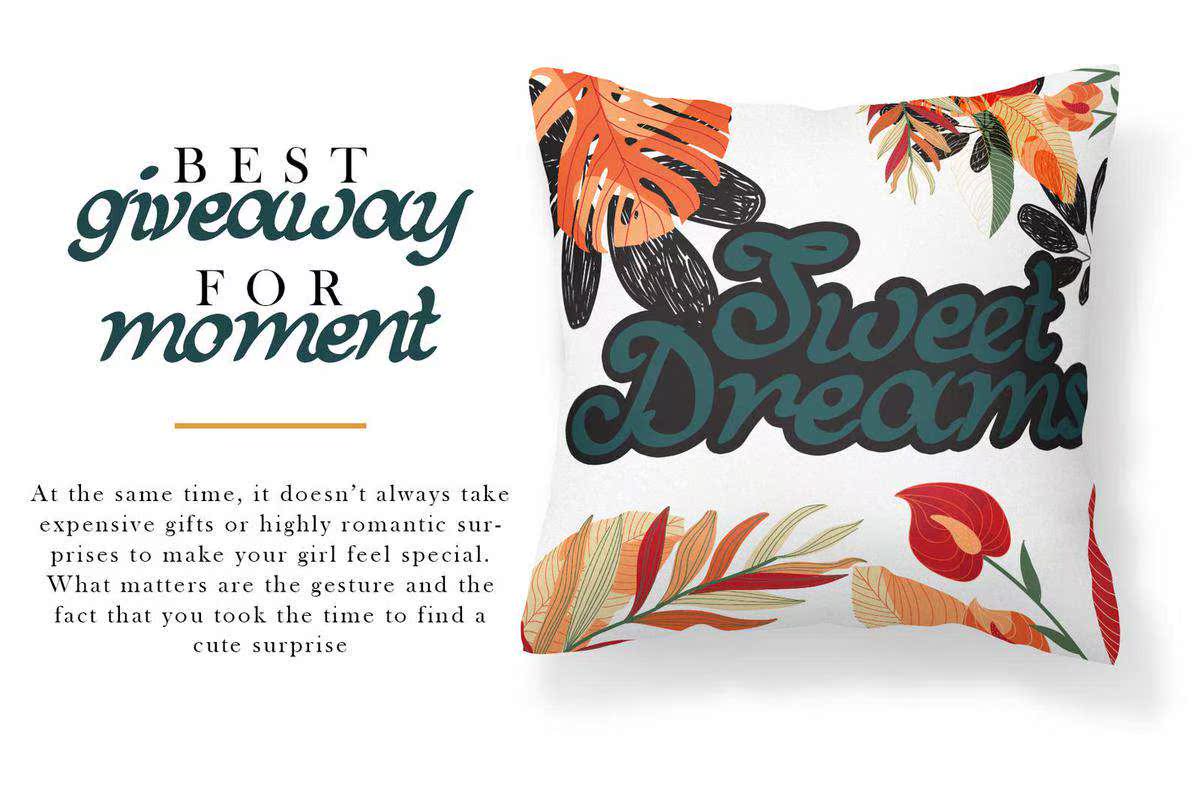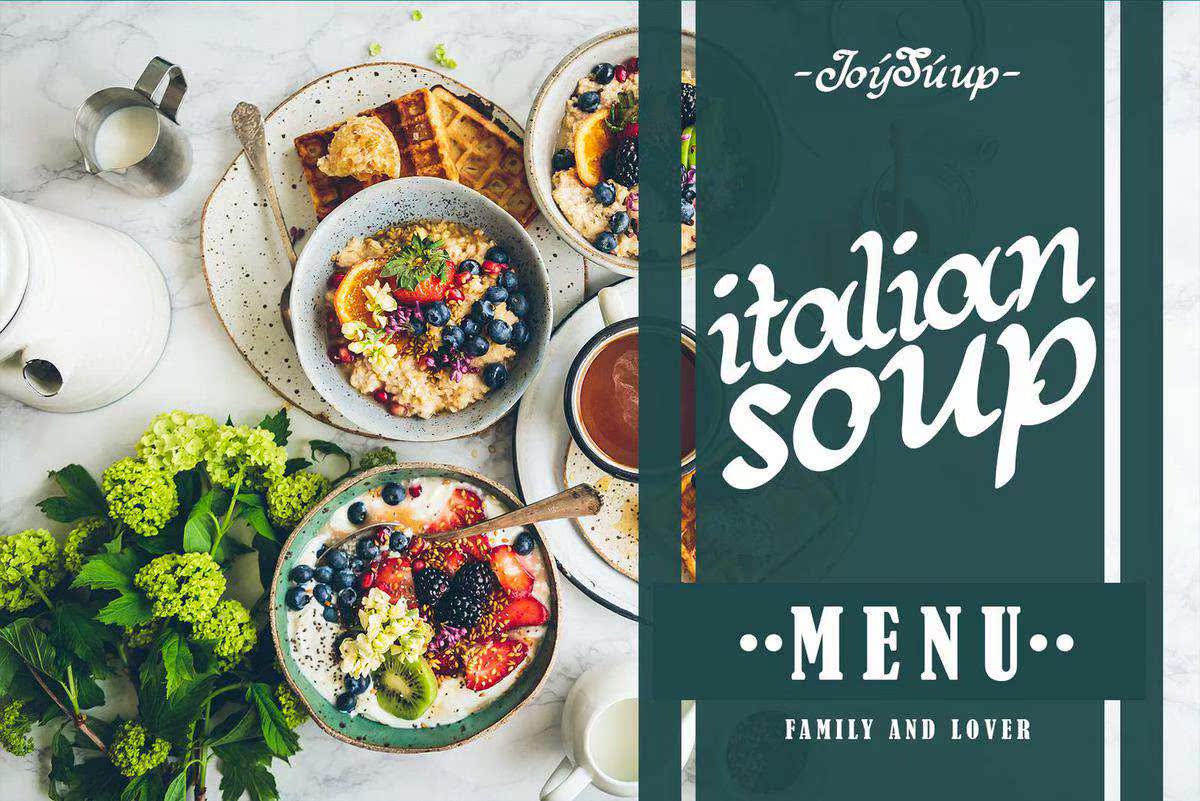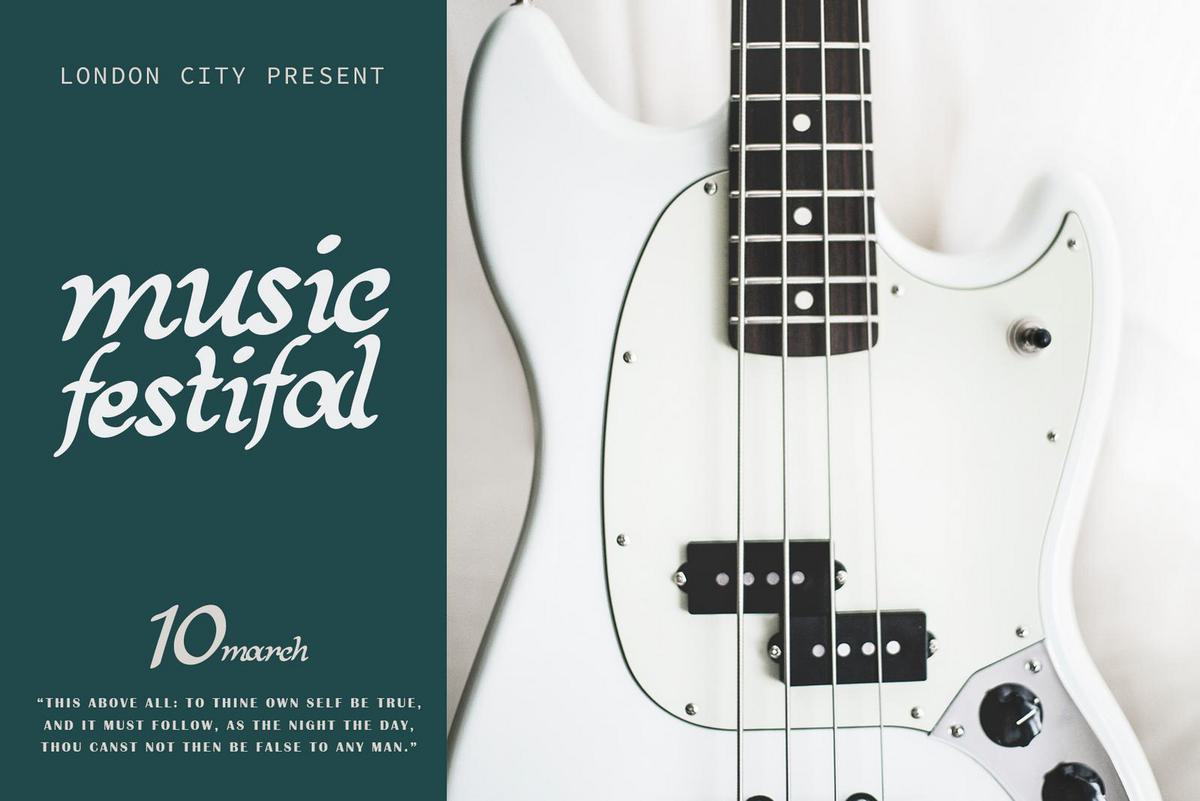
BreakoutScriptFont具有全新和现代风格。一套适合您的项目的文字和数字集合,适用于标识、品牌设计、标识设计、数字文字艺术、T恤/服装、海报、杂志、标志、婚礼宣传、生日邀请、广告设计、,和任何设计需求。使用全新和现代样式的BreakoutScriptFont。适合您的项目的文字和数字集合非常适合于标识、品牌设计、标识设计、数字文字艺术、T恤/服装、海报、杂志、标志、婚礼宣传、生日邀请、广告设计和任何设计需求。